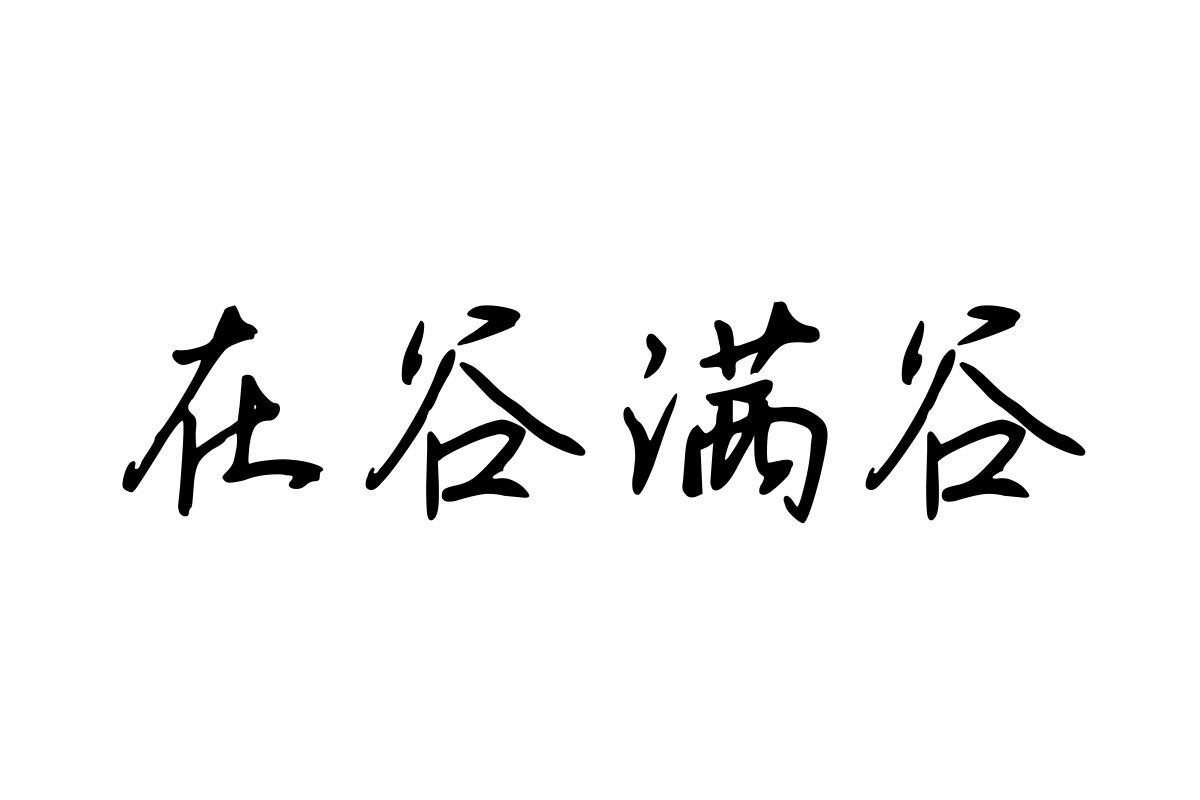
三极春临行楷是一套由书法家王冬龄创作的书法字体。这套字体以行楷为基础,融合了王冬龄的个性化风格和创新元素。
三极春临行楷的字形结构严谨,笔画流畅,线条粗细适中,具有很高的艺术价值。它的字体特点主要体现在以下几个方面:
1. 笔画流畅:这套字体的笔画流畅自然,没有生硬的转折和过度,给人一种轻松愉悦的感觉。
2. 结构紧凑:每个字的结构都紧凑合理,没有多余的空间,使得整个字体看起来更加整洁有序。
3. 线条粗细适中:这套字体的线条粗细适中,既不会过于粗犷,也不会过于纤细,使得整个字体看起来既有力度又不失柔和。
4. 个性鲜明:王冬龄的书法作品以其独特的个人风格而闻名,三极春临行楷也不例外。它充分体现了王冬龄的个性和创新精神,使得整套字体充满了活力和动感。
总之,三极春临行楷是一款具有很高艺术价值的书法字体,适合用于各种场合的宣传、展示和装饰。